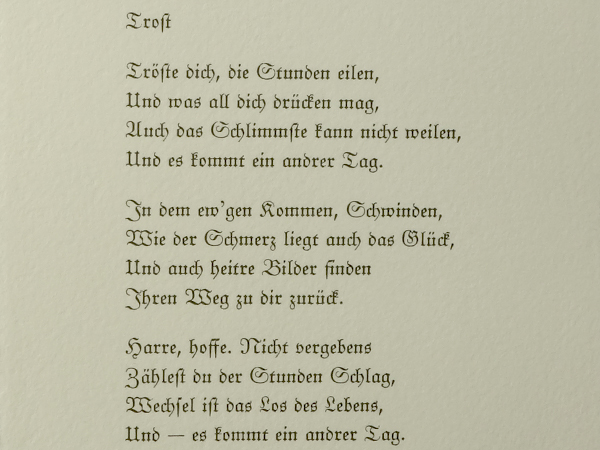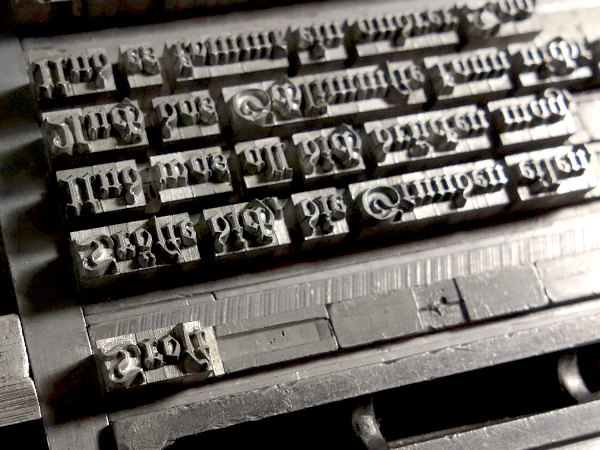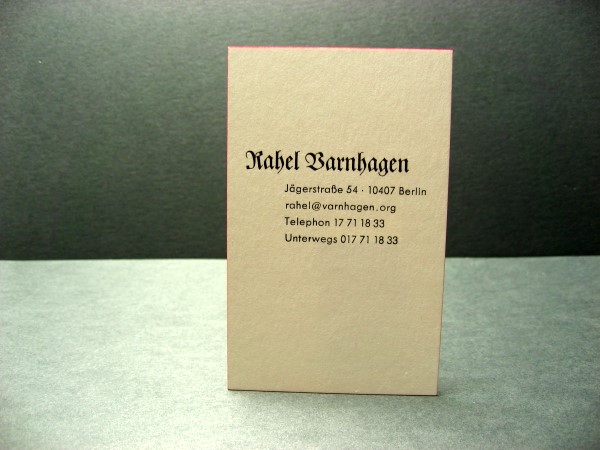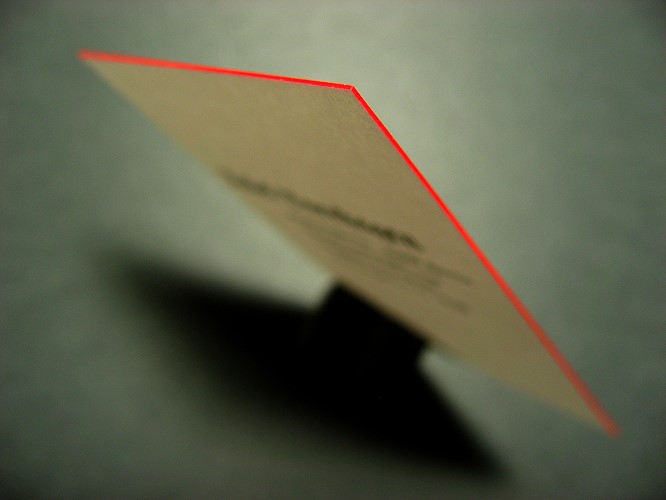
Langes s in heutigen Texten in gebrochener Schrift – notwendig, möglich oder unsinnig?
Ich versuche es mal radikal zu verkürzen, damit ich noch hinterher komme.¹
M: Die (große?) Mehrheit der heute gelesenen Fraktur-Texte folgt den in der ersten Hälfte des 20. Jahrhunderts üblichen Konventionen.²
R: Die (große?) Mehrheit der heute produzierten Fraktur-Texte folgt modernen Konventionen.
Meine Zwischenfrage: Schließen sich diese beiden Thesen notwendigerweise aus?³
Ableitend aus diesen Thesen scheint M zu empfehlen, auch heute produzierte Fraktur-Texte nach den Konventionen zwischen 1901 und 1950 zu setzen⁴. R hinterfragt diese Empfehlung und verteidigt zumindest die Legitimität von Anwendungen wie auf dem Spiegel-Titel und bei Gasthaus-Schildern.
Soweit alle(s) richtig verstanden? :-?
1. Wenn ihr meint, missverstanden worden zu sein, korrigiert mich. Aber bitte so knapp wie möglich!
2. weil Frakturtexte heutzutage überwiegend in damals veröffentlichten Büchern gelesen werden, die heutige Leser in heimischen/elterlichen Bücherregalen, Antiquariaten und Bibliotheken finden
3. Darüber, ob sie richtig oder falsch sind, könnt ihr ja streiten. Ich habe meine Vermutungen, wüsste aber nicht, wie man das einfach und verlässlich testen könnte. Aber ist das überhaupt wichtig? Beides (Fraktur produzieren und Fraktur lesen) sind winzig kleine Nischen.
4. weil das der Erwartungshaltung der (großen?) Mehrheit der Frakturleser entspräche und daher am wenigsten stören würde
Und ich würde folgendes Vorgehen empfehlen:
Möchte ich eine klassische Frakturschrift, welche auch die für viele, die es nicht gewöhnt sind, Fraktur zu lesen, schwierigen Buchstaben A, H, K, S, Z, k  und x enthält, würde ich auch das ſ verwenden, besonders wenn das s dieses Schwänzchen aufweist. Trotzdem würde ich eben moderne Rechtschreibung anwenden, und für ss am Wortende dieses nicht durch ß sondern durch ſs ersetzen.
Richte ich mich jedoch an Leser, die keinerlei oder nur sehr wenig Fraktur-Erfahrung mitbringen (oder einem gemischten Kreis, bei dem diese die Mehrzahl darstellen), würde ich nicht einfach nur auf das ſ verzichten, sondern so eine "Stilmöbel-Fraktur" wie die 21er Version der Unifraktur Maguntis verwenden, bei der es an Stelle des ſ ein schwanzloses s gibt. (es gibt übrigens auch bei den älteren Frakturschriften durchaus verschiedene, die schon die entsprechenden Buchstabenvarianten enthalten.
Wobei ich allerdings sagen muss, das mir in vielen dieser Modern-Frakturen die ersetzten Buchstaben nicht wirklich überzeugen
Hab das Gefühl der Strang ist lamgsam einer für den Esoterikparagraphen. Wenn die Fraktion, die Sympathie empfindet für die „traditionelle“ Satzweise aber eben auch jene nicht als blöd oder ungebildet abstempeln mag, die zeitgemäßen Satz für bestimmte Anwendungen nicht asuschließen mag und für letzteres auch gute Gründe anführt, wenn die also durch permanente Fehlinterpratationen genötigt wird, wieder und wieder Unterstellungen, Mißinterpretationen und Verdrehungen zu berichtigen, dann sind wir ja eh weit weg von einer fachlichen Diskussion, dann ist das eher eine Frage der Toleranzfähigkeit. Ralf plädiert hier nicht für die Ausrottung des lang-s. Er mag aber eben auch nicht jene pauschal als blöd hingestellt wissen, die, weil fachfremd, solche Nischendetails einfach nicht parat haben (können). Wenn man sich dann selber als Elite präsentiert weil man in seinem ureigenstem Metier einen jetzt gar nicht mal so wahnsinnig weltbewegenden Wissensvorsprung gegenüber Menschen anderer Profession hat, dann ist das für mich endgültig keine fachliche sondern eben eine charakterliche Frage.
Ich antworte direkt auf Þorstens Fragen:
Zitat: »M: Die (große?) Mehrheit der heute gelesenen Fraktur-Texte folgt den in der ersten Hälfte des 20. Jahrhunderts üblichen Konventionen.²«
Das ist inklusive Fußnote richtig.
Zur Zwischenfrage: Ich bestreite, daß es heute eine solche Übereinkunft gibt. Das druckfrische Büchlein »Wie ich Bücher gestalte« von Friedrich Forssman (Wallstein-Verlag) ist in alter Rechtschreibung gesetzt. Zeitungen und Verlage pflegen individuelle Hausrechtschreibungen oder überlassen die Rechtschreibungen ihren Autoren, die sich aus verschiedenen Rechtschreibregelwerken bedienen. Es gibt zur Zeit nicht eine Rechtschreibkonvention, sondern diverse.
Was den letzten Absatz (»Ableitend aus diesen Thesen (...)«) angeht, gibt auch er meine Position richtig wieder.
Zur Zwischenfrage: Ich bestreite, daß es heute eine solche Übereinkunft gibt.
Mir ist nicht ganz klar, welche »Übereinkunft« du meinst. (Mir war nicht bewusst, dass ich eine solche in den Raum gestellt hätte. :-?)
Glaubst du, dass die Mehrheit heutzutage produzierter Fraktur-Anwendungen den Konventionen von 1925 (±¼ Jh.) folgt?
@Ralf: Erstens habe ich nie behauptet, du gehörtest zu den Fraktur-Gegnern. Zweitens gehöre ich nicht zu den Fraktur-Befürwortern, die nur die Verwendung der Fraktur als einer Schrift (script) mit ihren eigenen typografischen Regeln für richtig erachten.
Der Konflikt liegt darin, dass einige an einem bestimmten historischen Konventionsstand festhalten möchten, in der Realität aber etwas anderes passiert. Dann gegen mich zu argumentieren ist sinnlos, weil ich diese Realität nur beschreibe und nicht beeinflusse. Ich könnte es auch gar nicht. Selbst wenn ich alle Typografie.info-Mitglieder schwören ließe, fortan gebrochene Schrift nur noch mit langem s zu setzen – es würde nichts ändern. Das ſ verschwindet dennoch aus der deutschsprachigen Fraktur.
Für sinnvoll halte ich das auch nicht, weil man dadurch eine Volks- und eine konkurrierende Staatsschreibung hat
1. Esoterik! Der böse, böse, willkürliche Staat mal wieder, der sich mit dem Volk (und seinem per se gesunden Empfinden) anlegt. Ist es wirklich so schwer zu verstehen, dass du in einem demokratisch verfassten Staat für diesen genauso viel Verantwortung trägst wie Ralf? Oder ich? Oder jeder andere?
2. Es gibt also eine Volksschreibung? :mrgreen: :mrgreen: